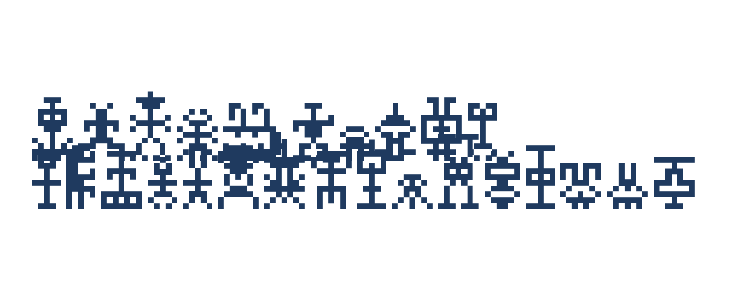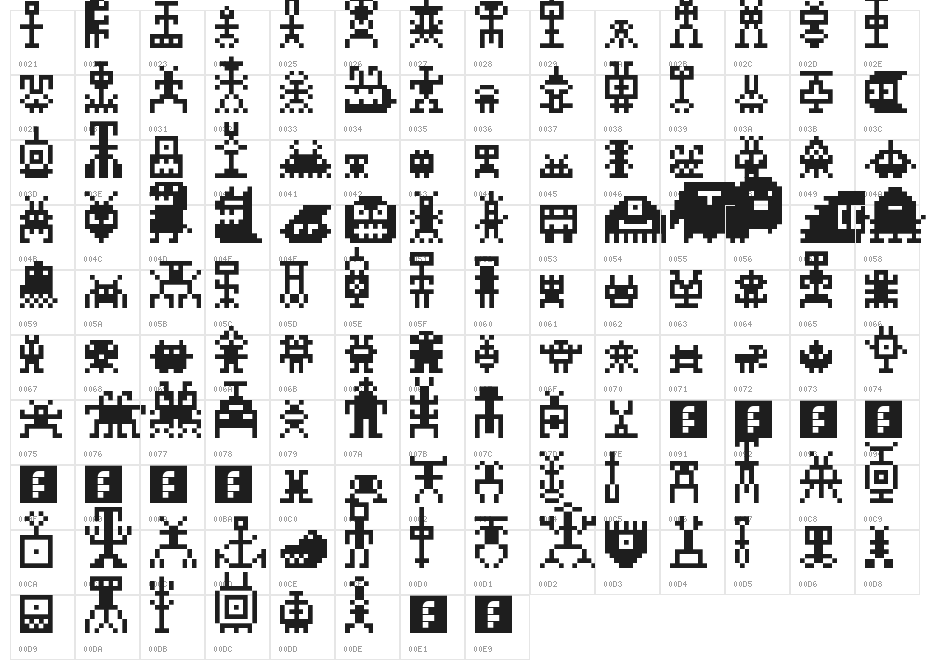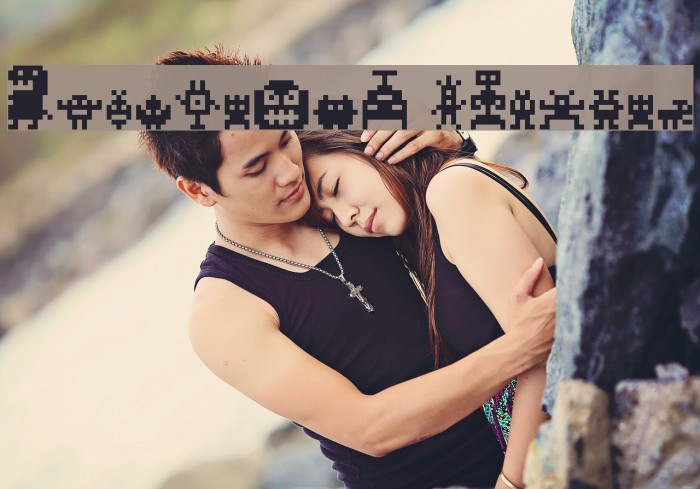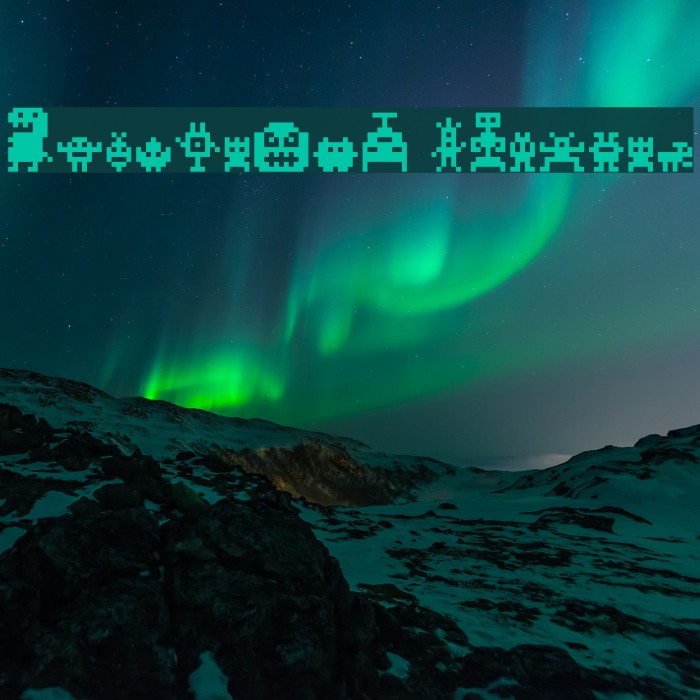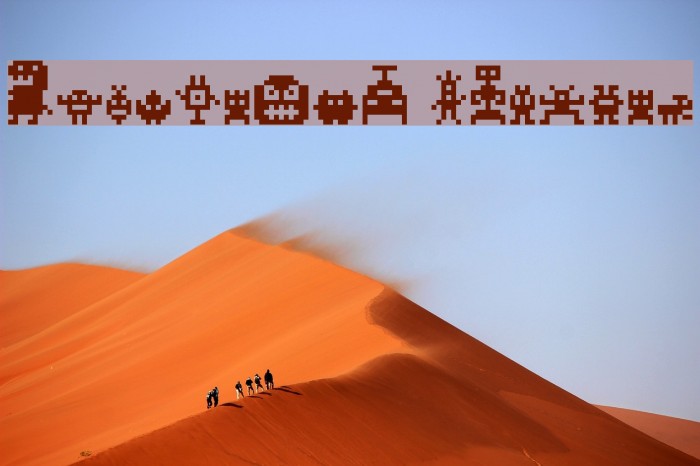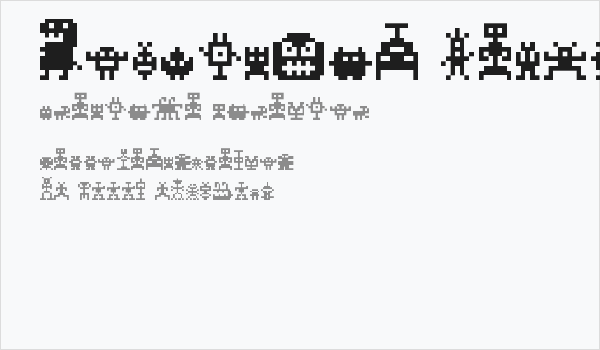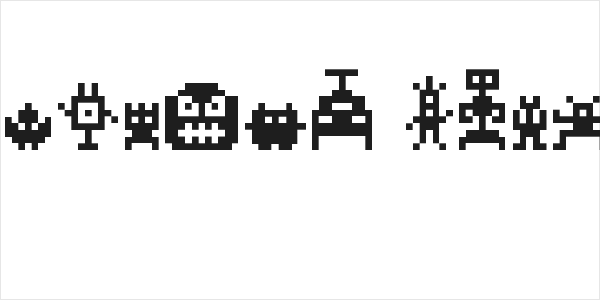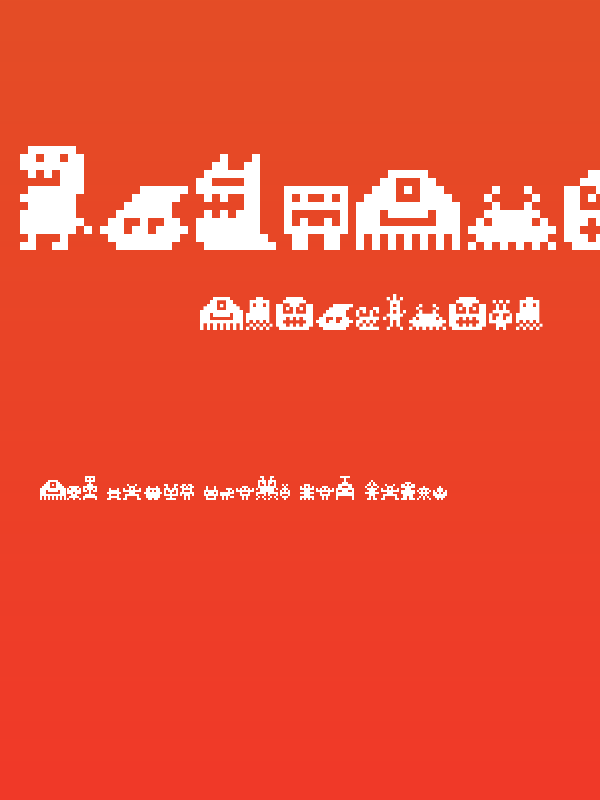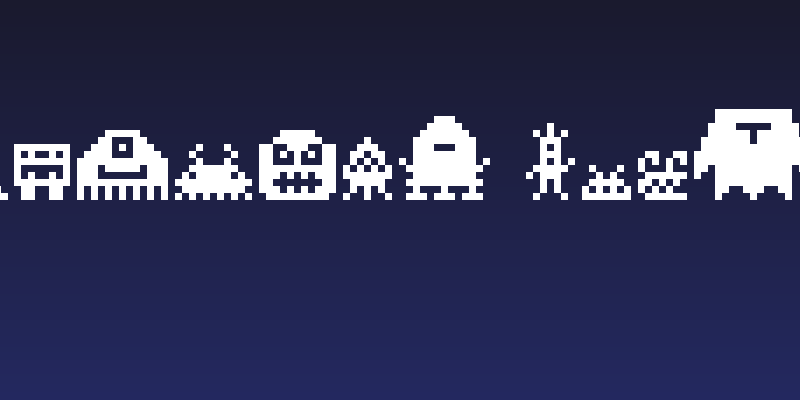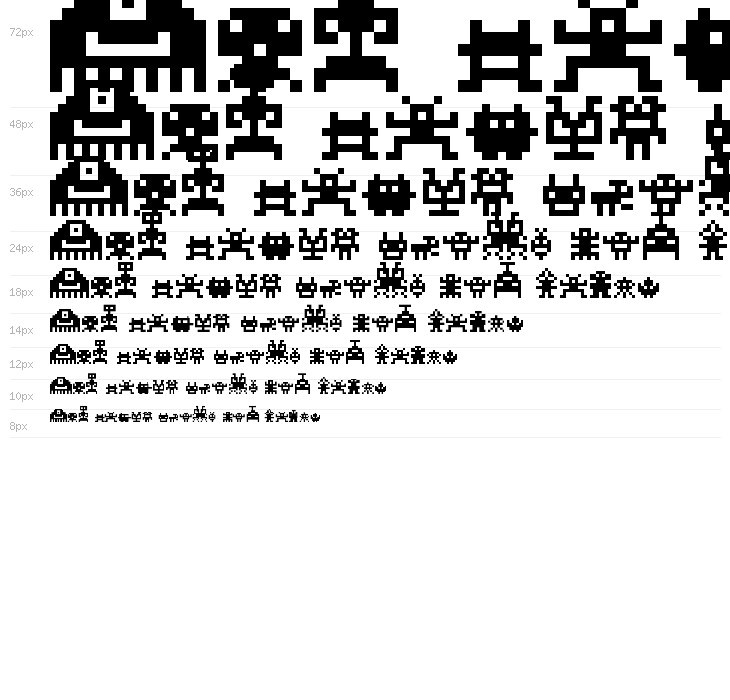
MonstaPix Regular Font
| Stile generale | Retro, Playful |
| Caso d'uso | Logos, Posters, Themed Graphics |
| Progetti proposti | Ideal for video game designs, children's book illustrations, themed party invitations, or any creative project needing a playful touch. |